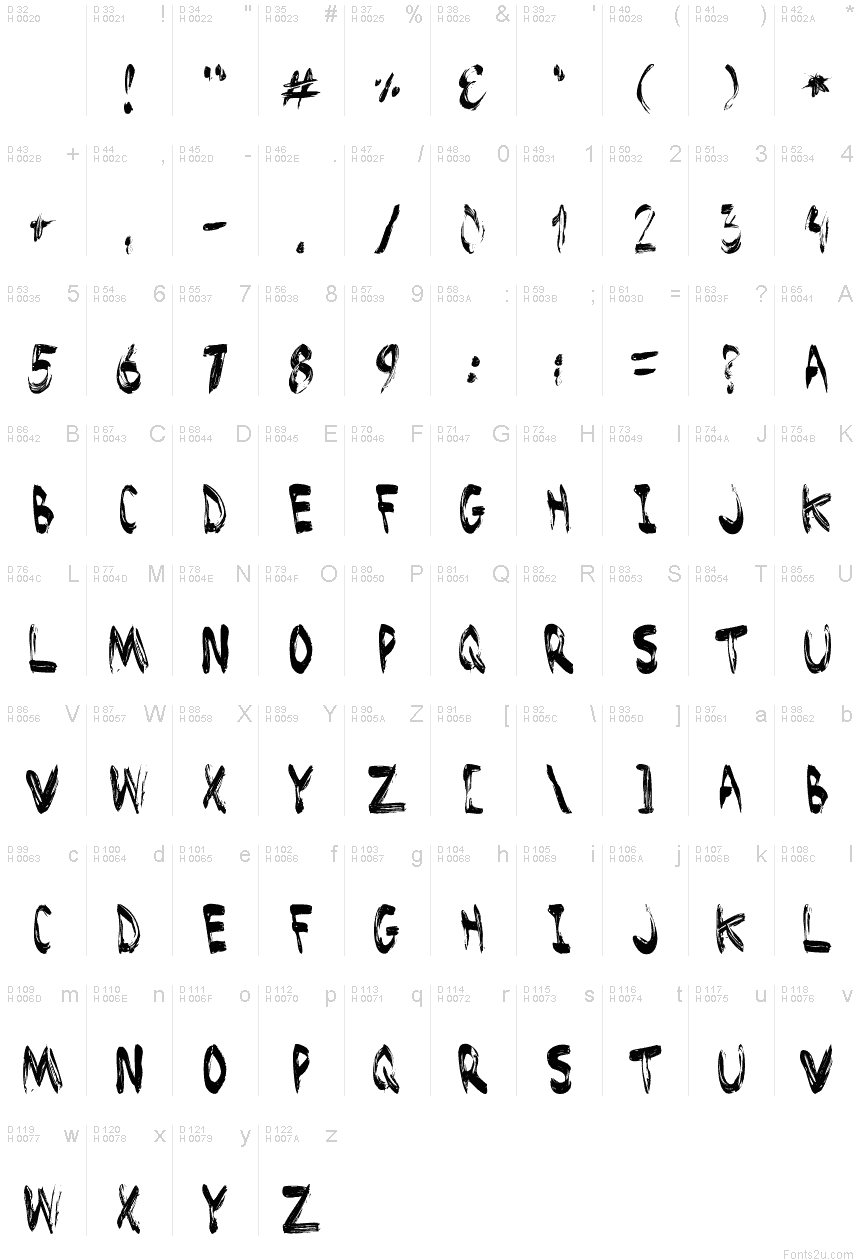
Brushed от Якоба Фишера — это бесплатный кистевой шрифт, который выглядит так, словно его провели по бумаге кистью, обильно пропитанной чернилами. Толстые мазки разлетаются царапающими брызгами, а неровные края и полосы создают ощущение сырой, ручной работы, а не отполированного дизайна. Буквы наклоняются и изгибаются ровно настолько, чтобы добавить дерзости, придавая заголовкам шумную, энергичную текстуру, которая буквально выпрыгивает из фона.
С помощью Brushed вы можете добавить драйва постерам к концертам, названиям хорроров или триллеров, стритвир-графике, скейтерским и панк-флаерам, броским баннерам для соцсетей и цепляющим превью для YouTube. Этот бесплатный шрифт лучше всего раскрывается в крупном кегле, где видны все детали ворсистого мазка, и отлично сочетается с чистым, простым гротеском в качестве вспомогательного текста.